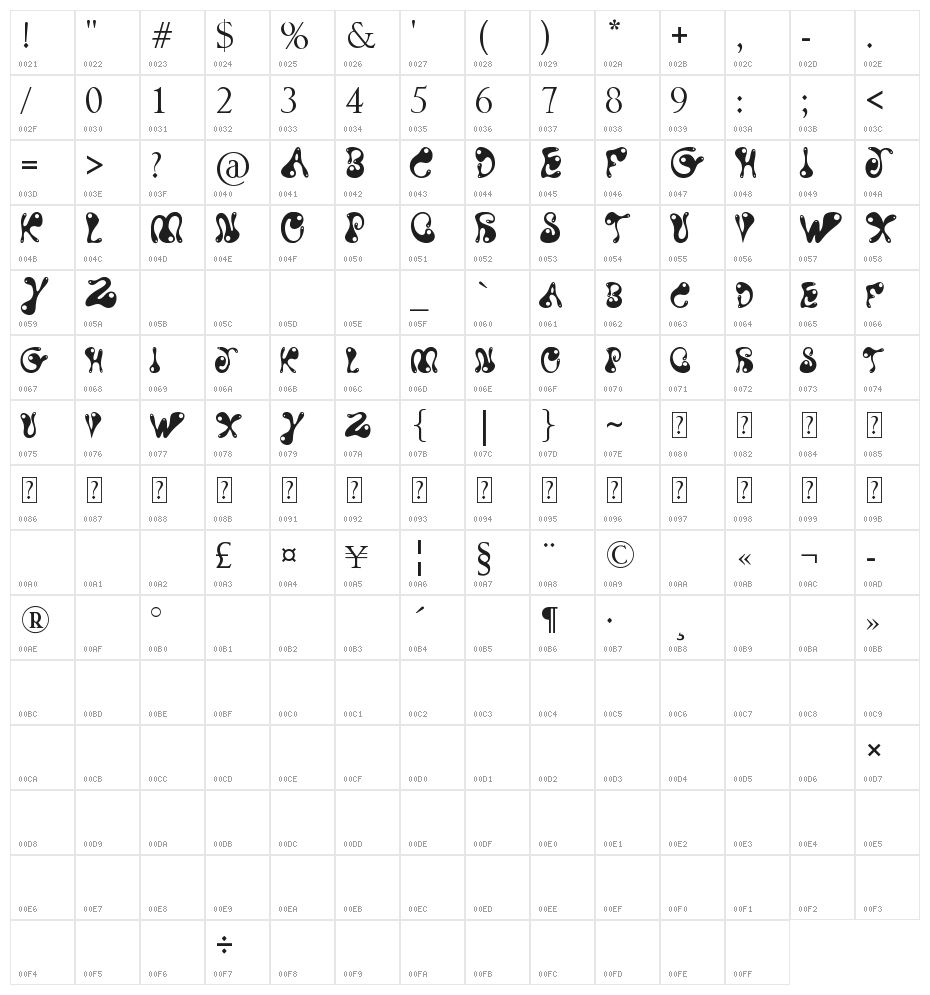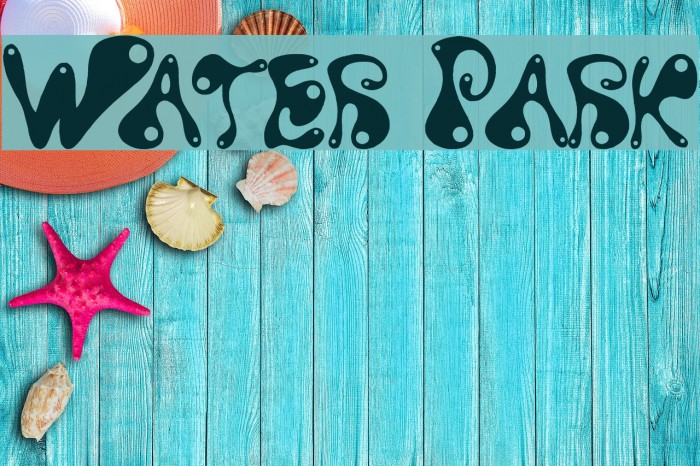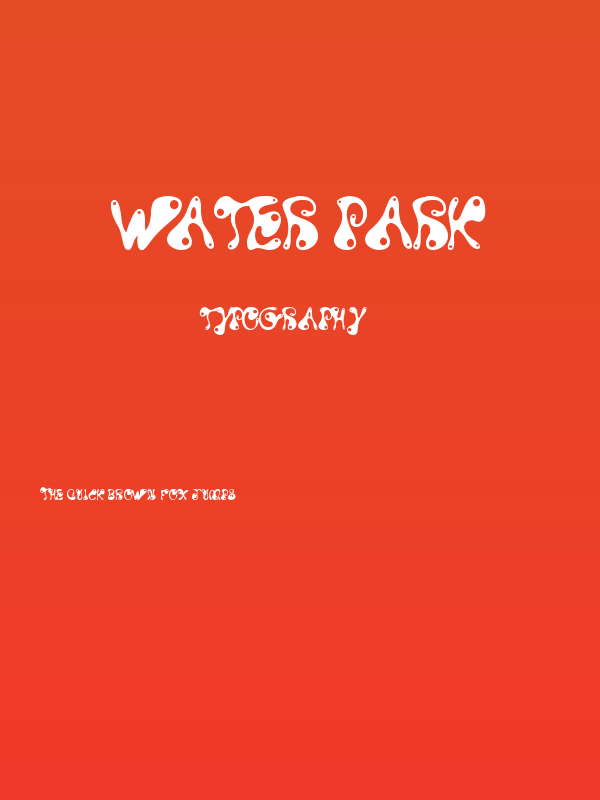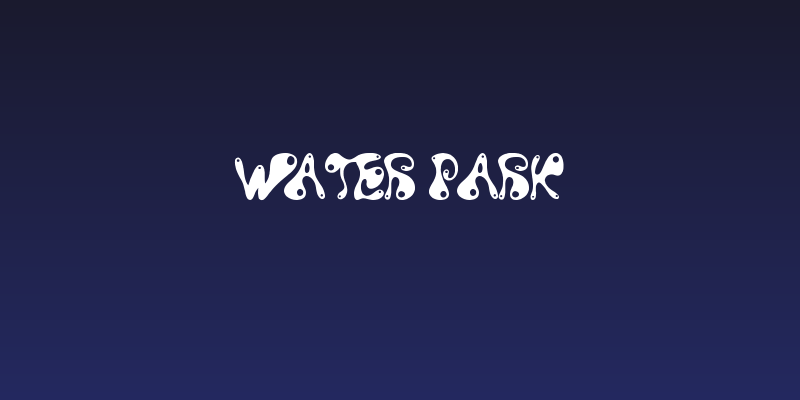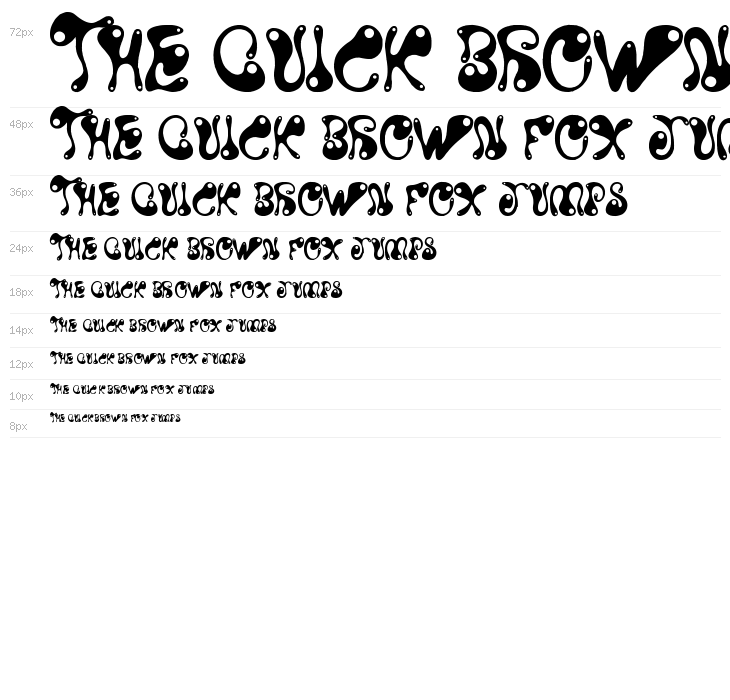
Water Park Font
| 使用场景 | Logos, Headlines, Posters |
| 推荐项目 | Perfect for children's books, water park branding, playful event posters, or any project needing a whimsical touch. |